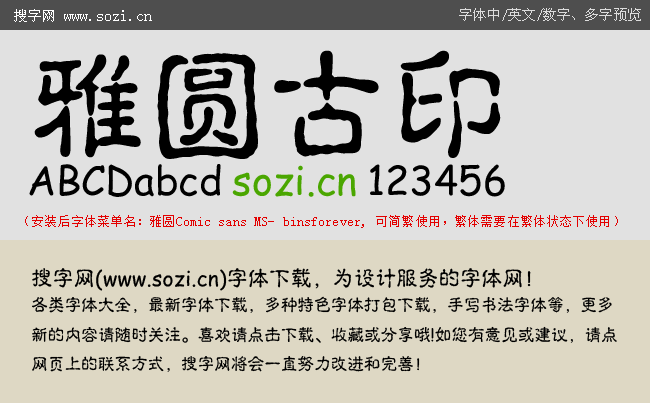
雅圓古印
搜字網(wǎng)給大家提供一款雅圓古印中文藝術(shù)字體下載。雅圓古印字體 是一款設(shè)計非常復(fù)古具有獨特韻味的字體,雅圓古印字體圓潤、美觀,可用畫冊設(shè)計、平面設(shè)計、印刷包裝、報紙雜志等廣告設(shè)計場合使用。
• 風(fēng)格類別: 古印體